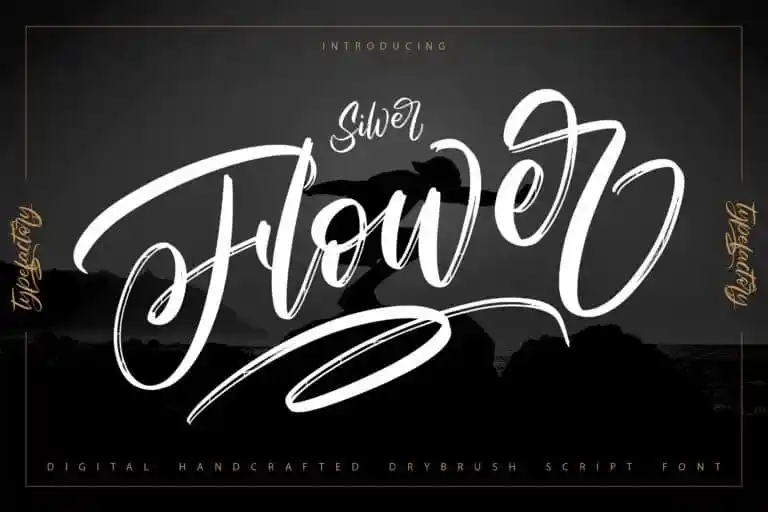
A Silver Flower Brush Font é uma elegante tipografia de script criada por um designer chamado Type Factory, inspirada nas linhas urbanas modernas mas com letras finas e belas que transmitem sofisticação. Esta fonte se destaca pela sua beleza aparente e sofisticada forma, tornando-a ideal para expressar personalidade nas criações de design gráfico ou publicitário. Perfeita para criar frases destacadas, logos, títulos e capas de livros, a Silver Flower Brush Font também oferece um toque elegante que se adapta perfeitamente às páginas de revistas modernas. Ela é uma opção ideal para designers buscando incorporar estilo e sofisticação em seus projetos, sem comprometer o impacto visual ou a legibilidade da tipografia.